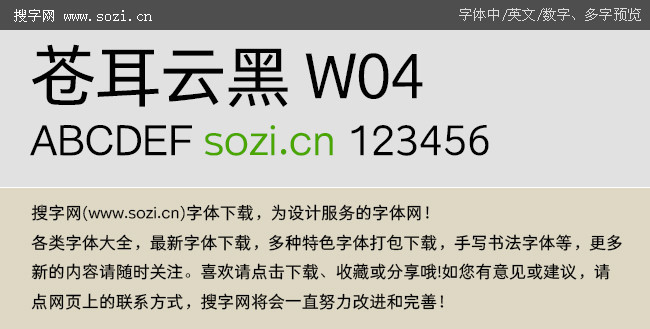
蒼耳云黑W04
搜字網(wǎng)給大家提供一款蒼耳云黑W04中文字體下載,倉(cāng)耳云黑是中國(guó)第一款突破鉛字黑體束縛的原創(chuàng)黑體,在同類產(chǎn)品中筆形特征典雅現(xiàn)代,結(jié)體豐富容易辨識(shí),獨(dú)具匠心的筆畫與結(jié)構(gòu)的微妙結(jié)合體現(xiàn)出黑體獨(dú)有的字形之美,展現(xiàn)漢字所具有的多變、精巧的靈韻之美。適合應(yīng)用于藝術(shù)設(shè)計(jì)、平面宣傳設(shè)計(jì)、網(wǎng)頁(yè)設(shè)計(jì)等應(yīng)用。(本字體為個(gè)人非商用版,如需要商用請(qǐng)聯(lián)系官方購(gòu)買版權(quán))